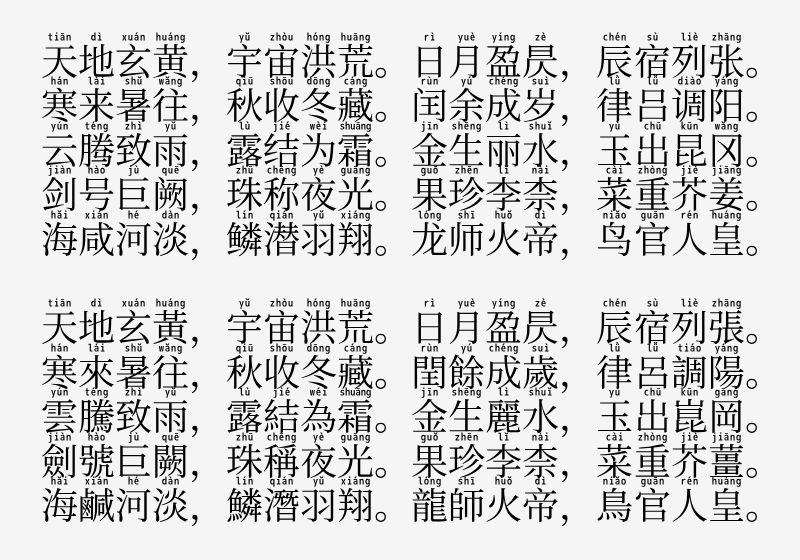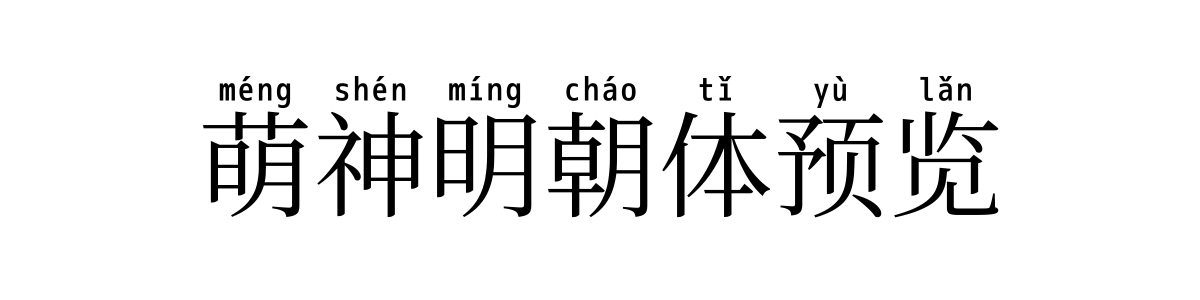
萌神明朝体
萌神明朝体(Mengshen Pinyin Font)是一款基于思源宋体M+ FONTS 改造的字体,专为汉语学习者设计。它不仅支持基础日文、简体中文及繁体中文显示,更创新性地为每个汉字添加了拼音注音功能。
这款字体通过 OpenType 特性实现了上下文替换功能,能够智能识别并正确显示多音字的拼音。同时支持 Unicode IVS 表意文字变体选择器,可以手动切换不同的拼音显示方式。
字体风格
萌神明朝体的设计核心在于教育功能与美学表现的完美融合。在继承思源宋体优美字形的基础上,精心设计了与每个汉字匹配的拼音注音布局,确保拼音显示清晰可读且不影响原文排版效果。其智能多音字处理系统能够根据语境自动选择正确的拼音。